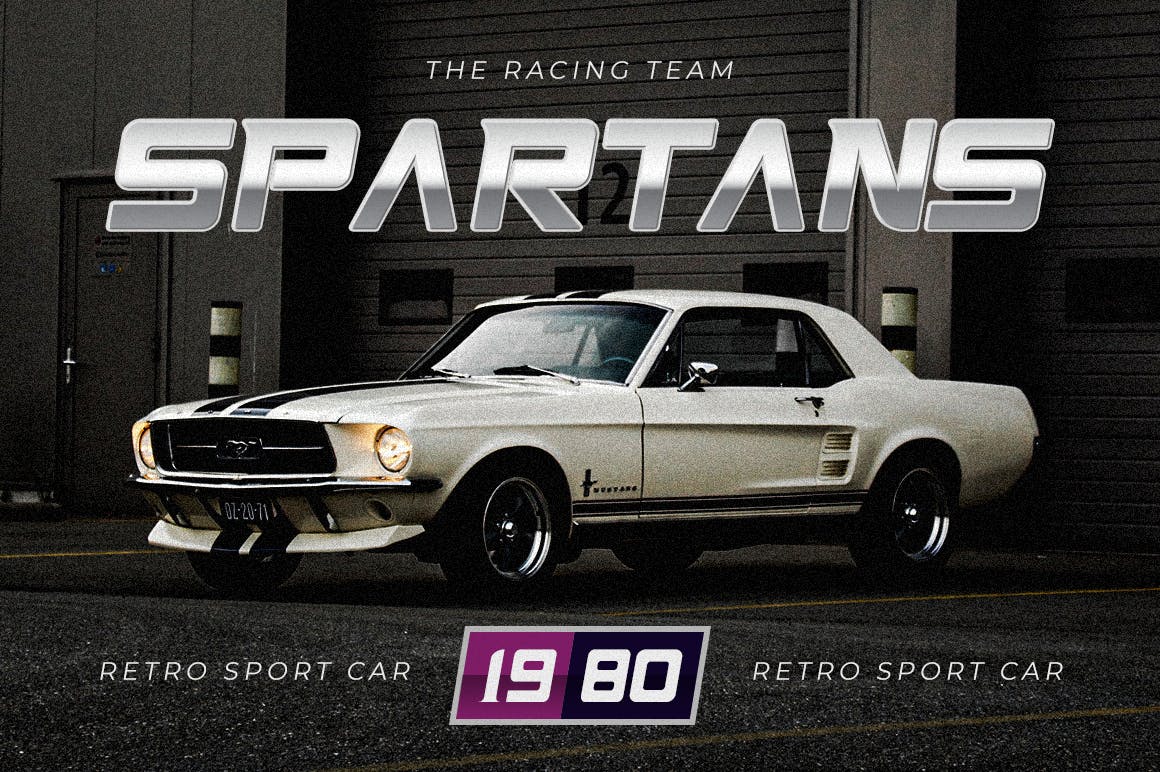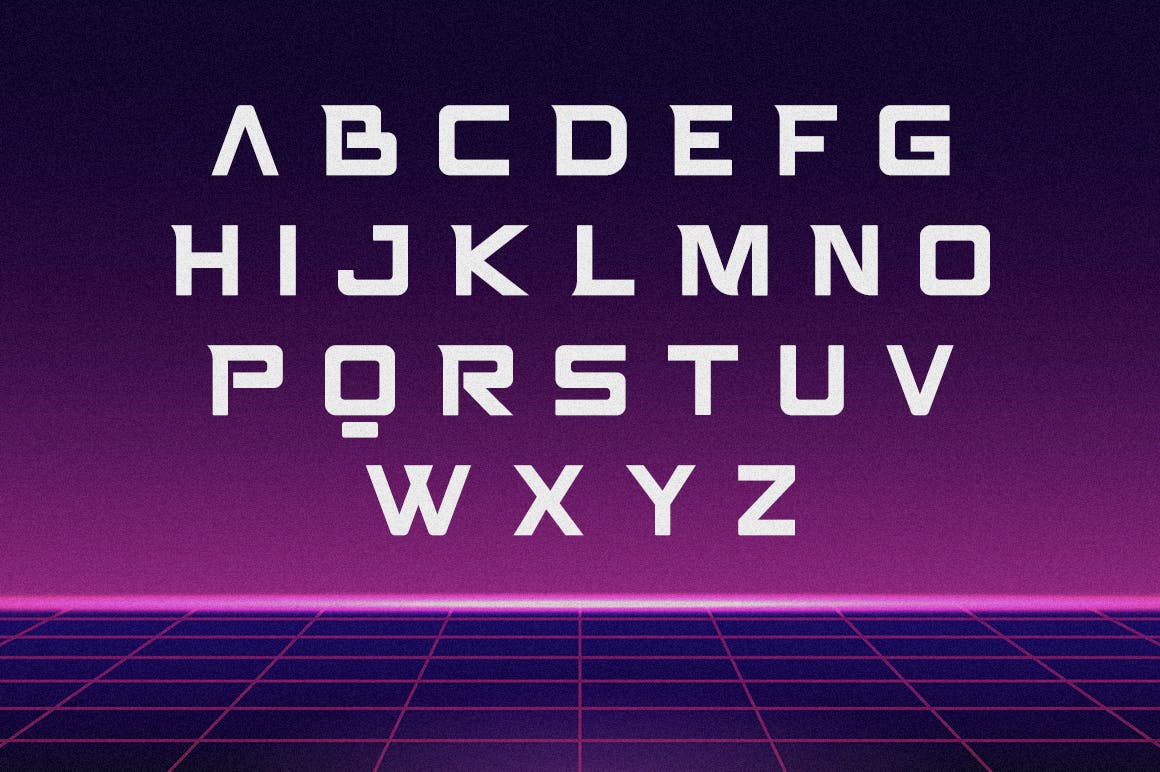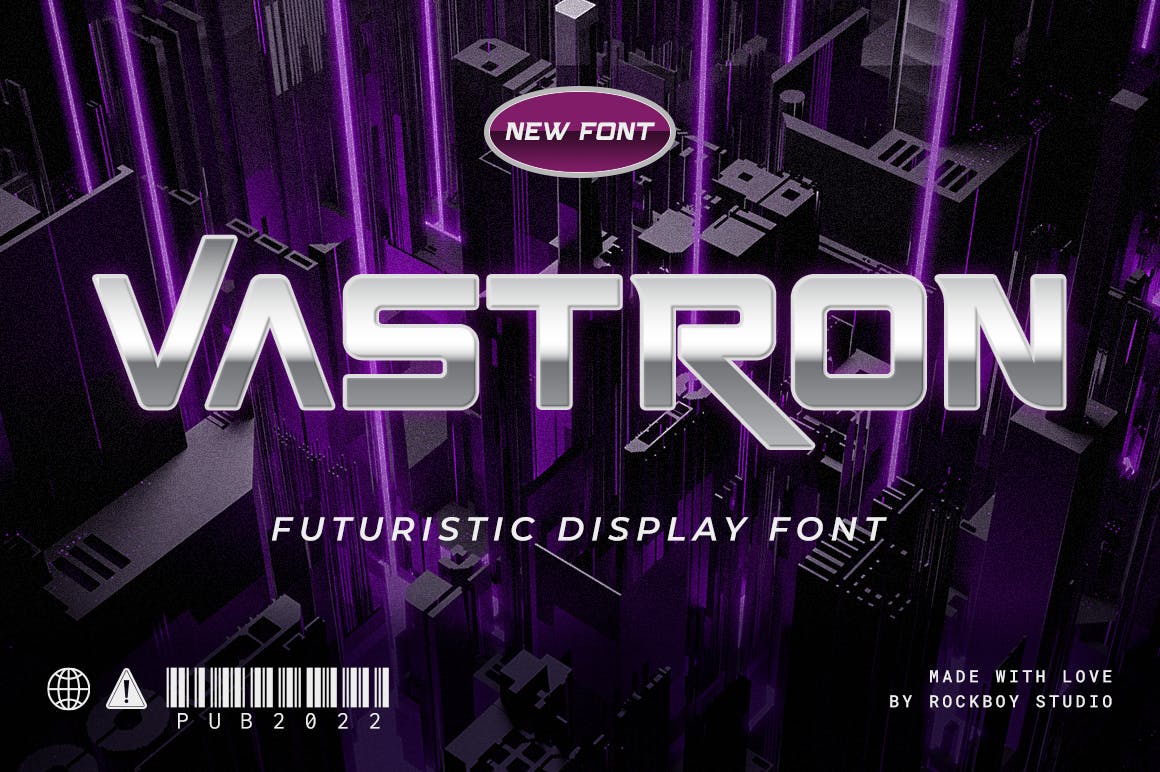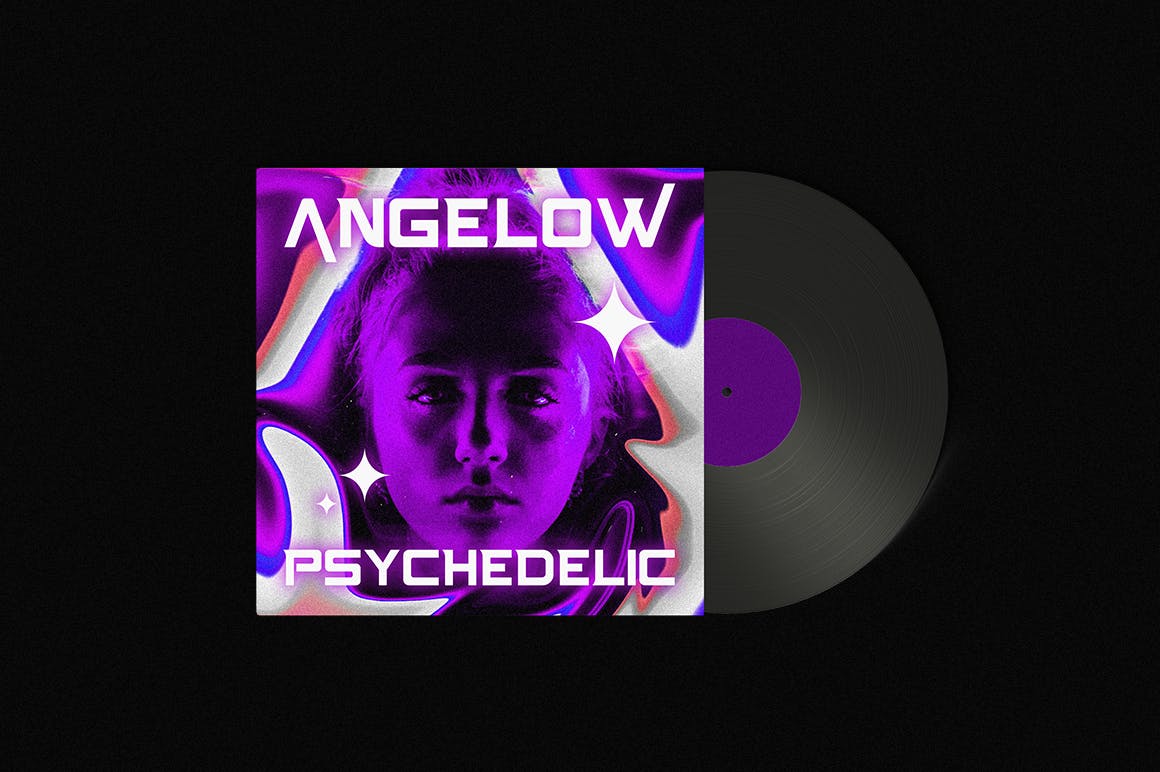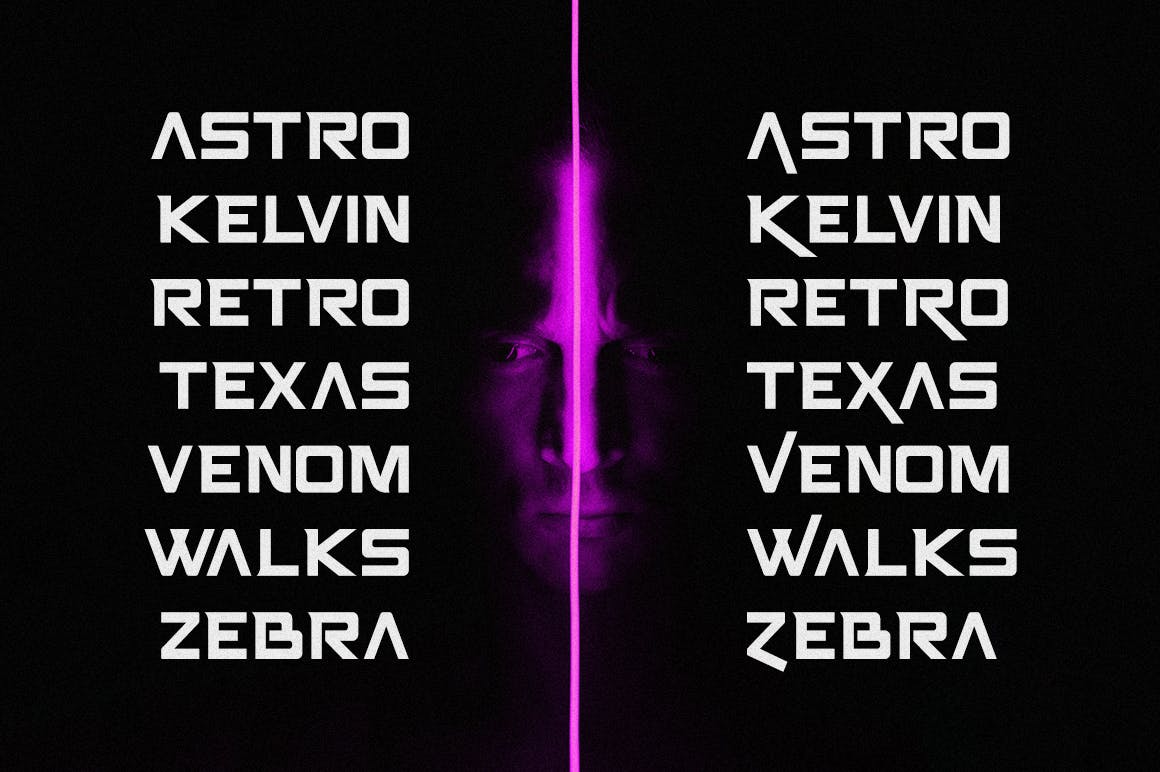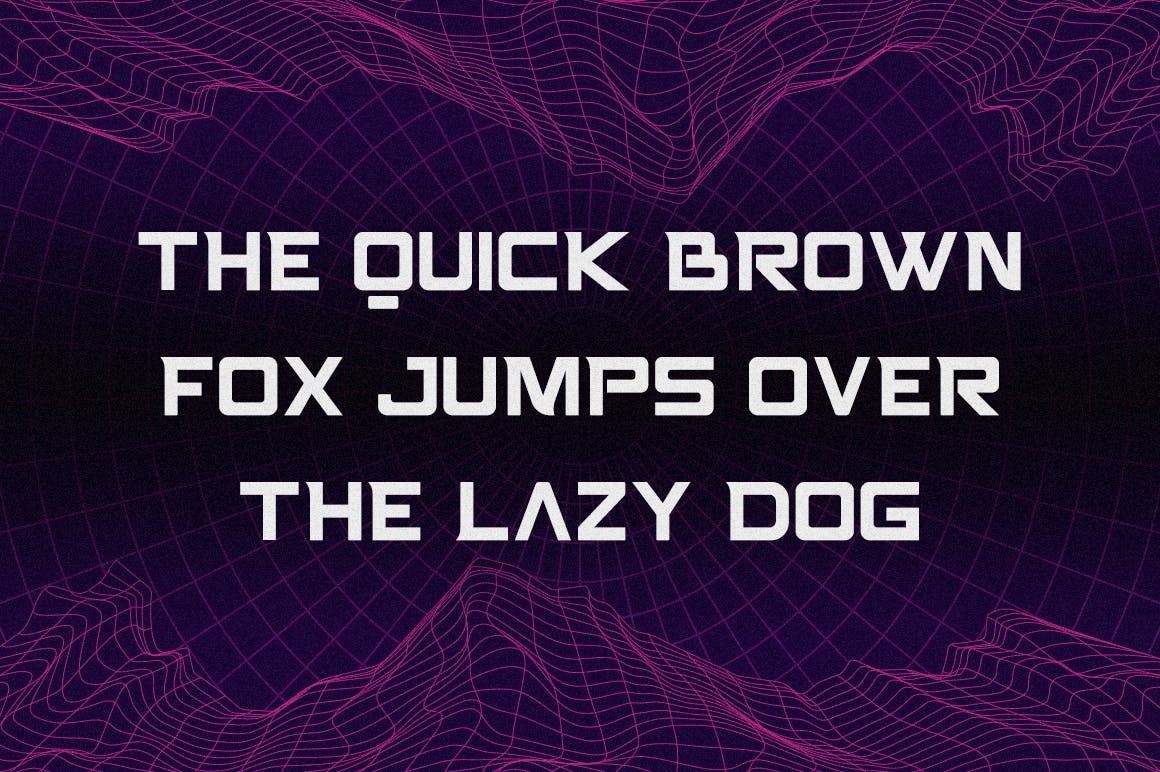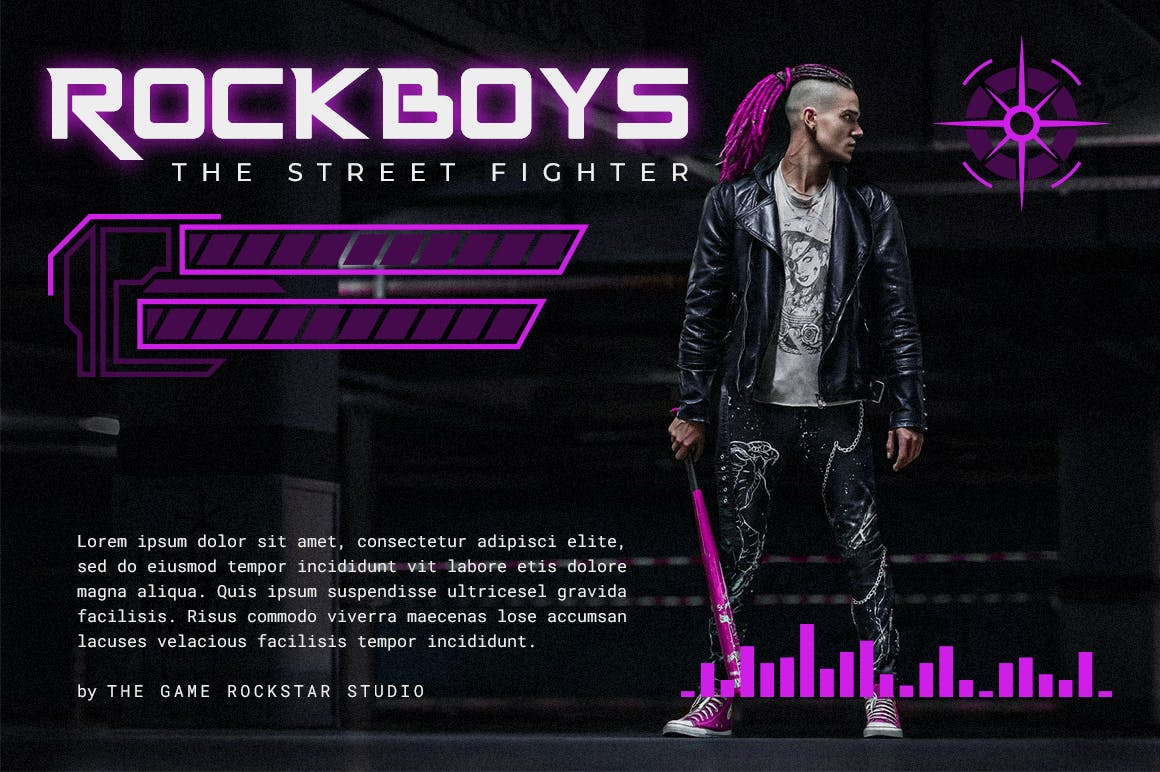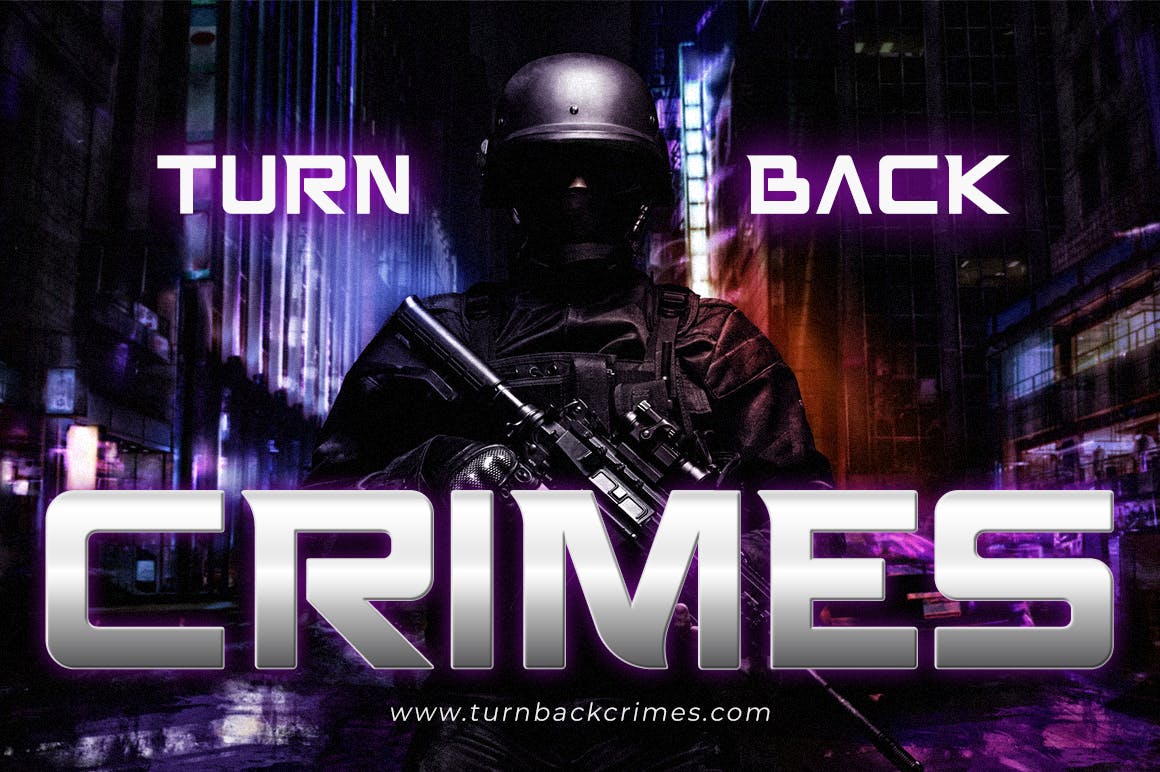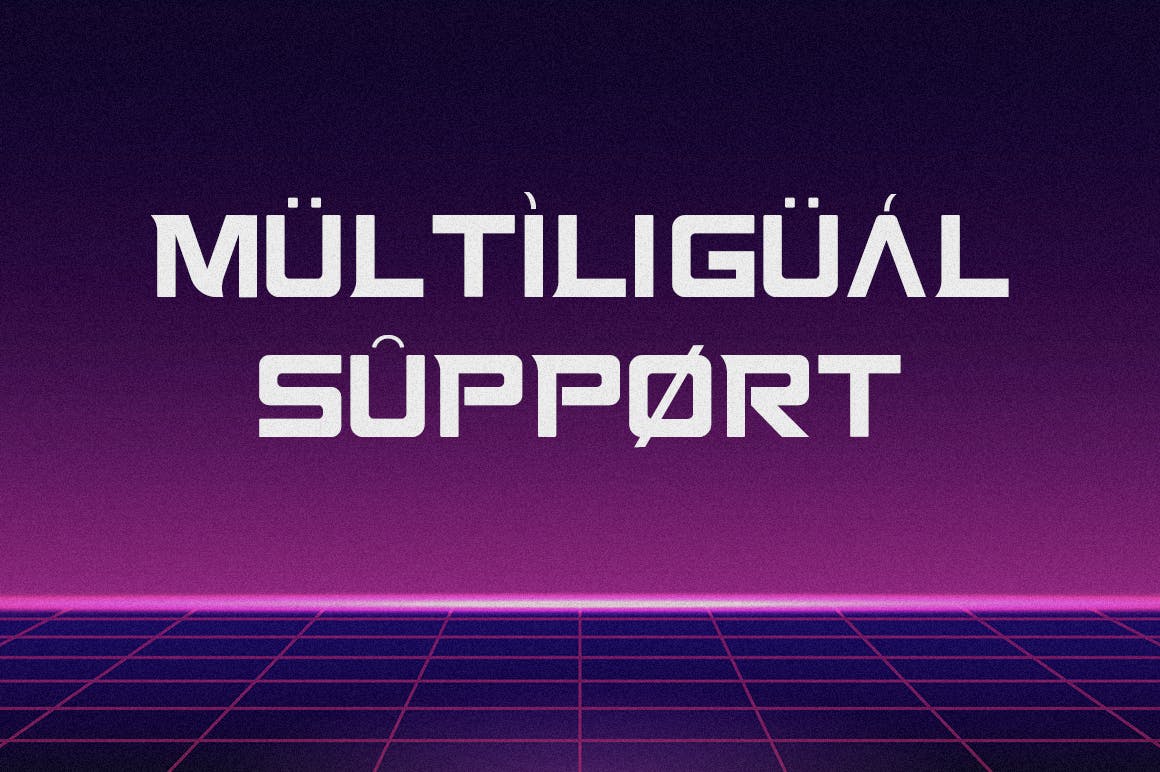
فونت Vastron یک فونت بدون سرف (sans serif) با طراحی خنک، جسورانه و حروف ضخیم است. این فونت میتواند ایدههای مختلفی را برای طراحی، از کارتها گرفته تا برندسازی، برچسبها و بسیاری موارد دیگر ارتقا دهد. با استفاده از این فونت در پروژههای خلاقانهتان، آنها را به آثار فوقالعادهای تبدیل کنید!